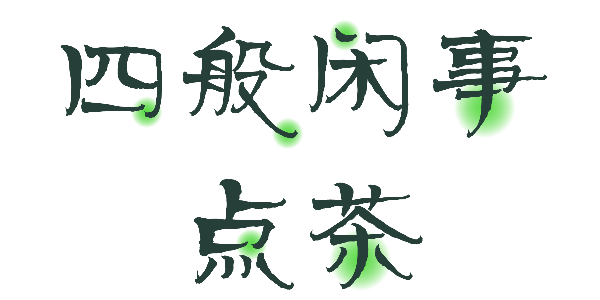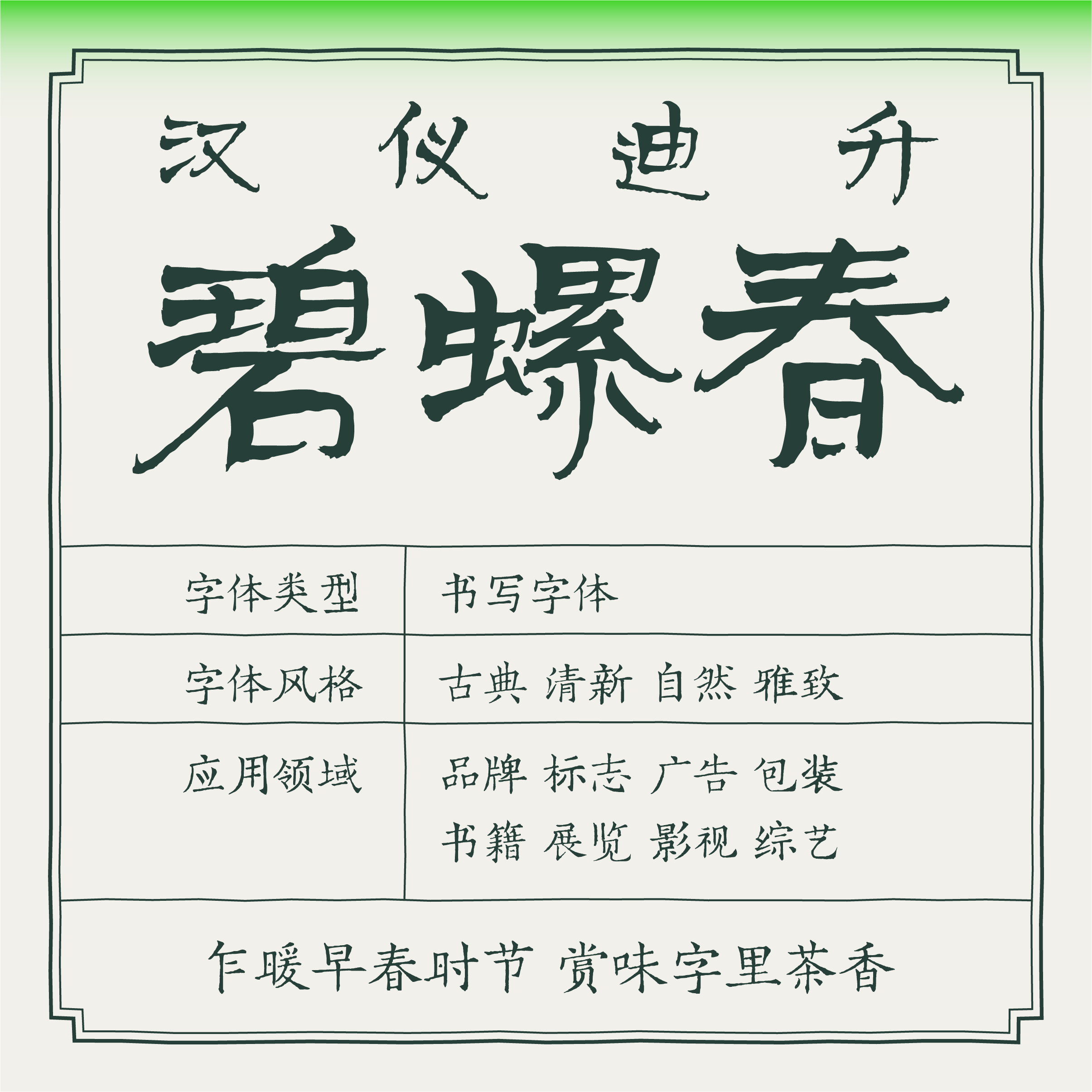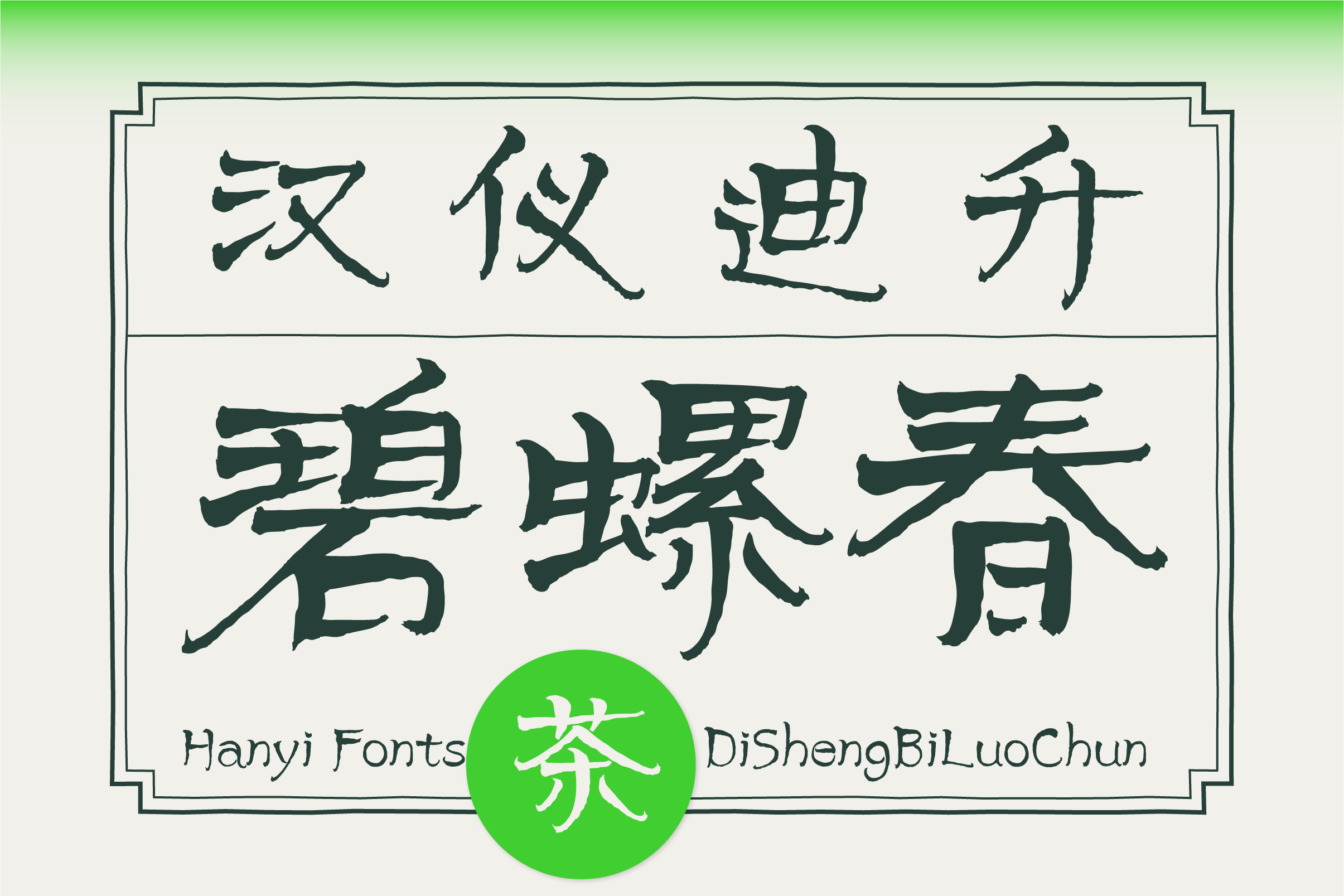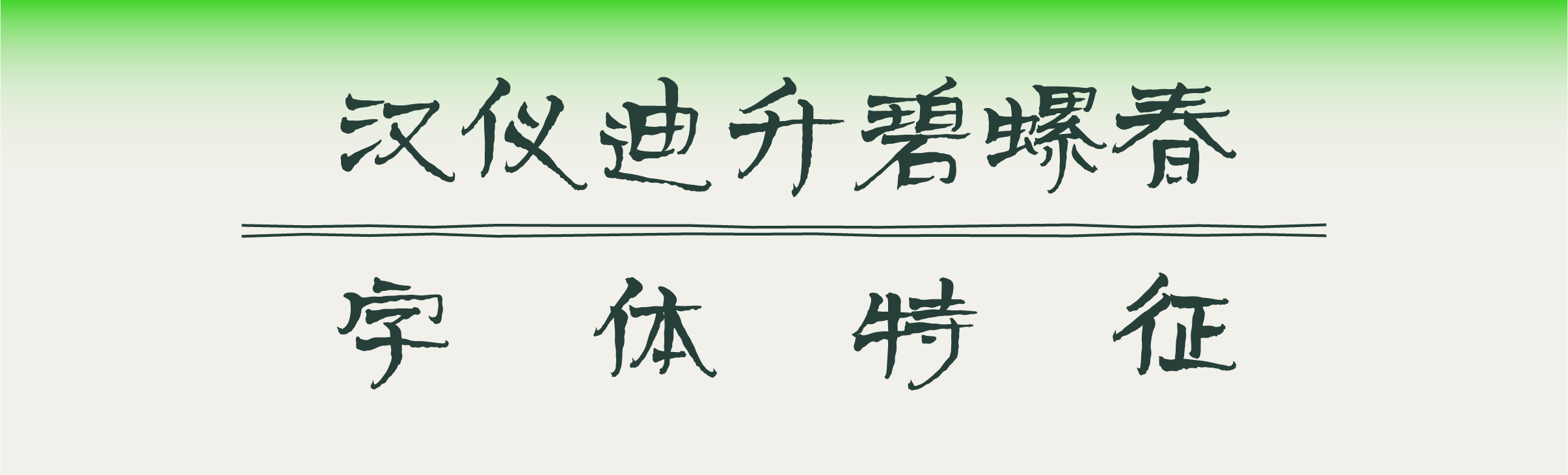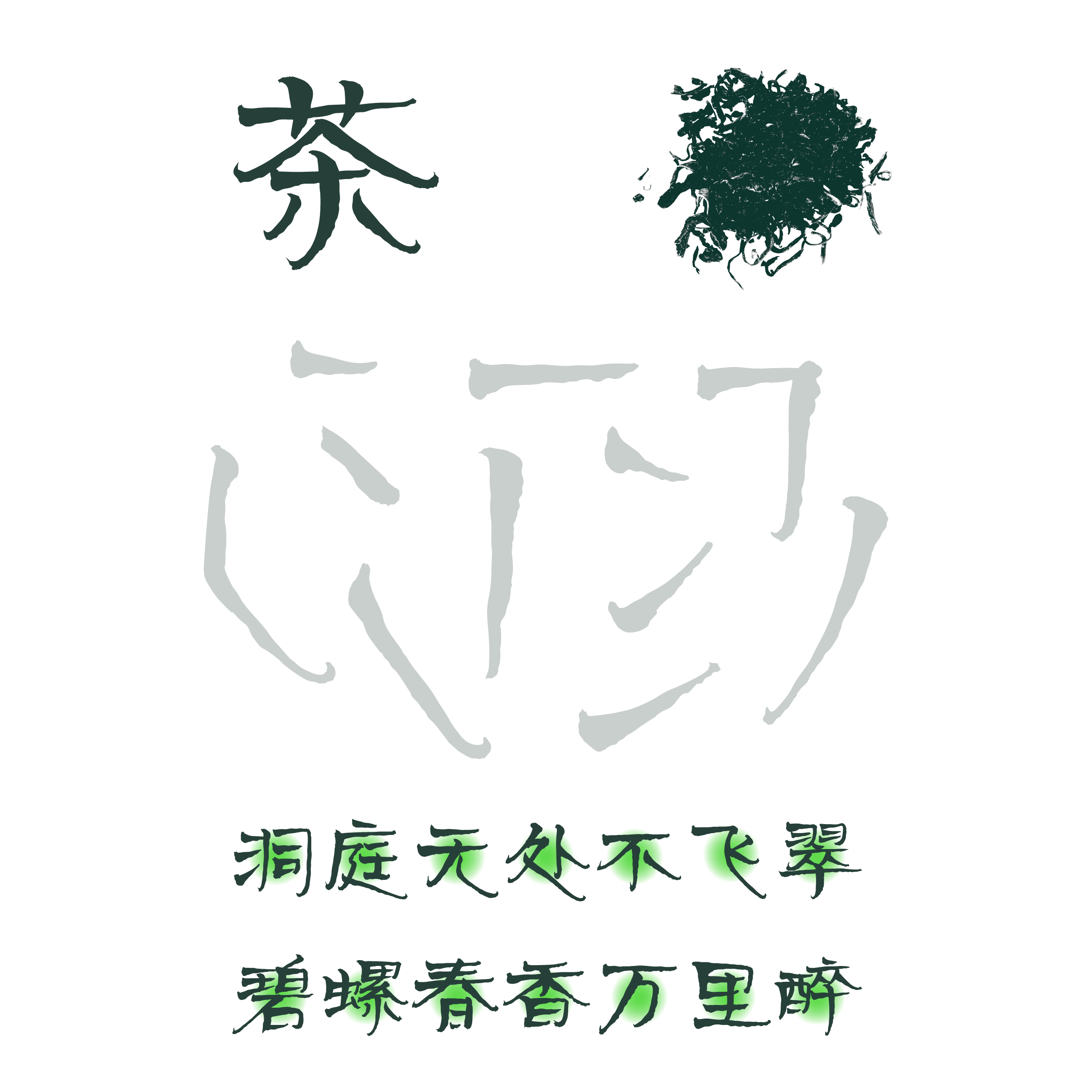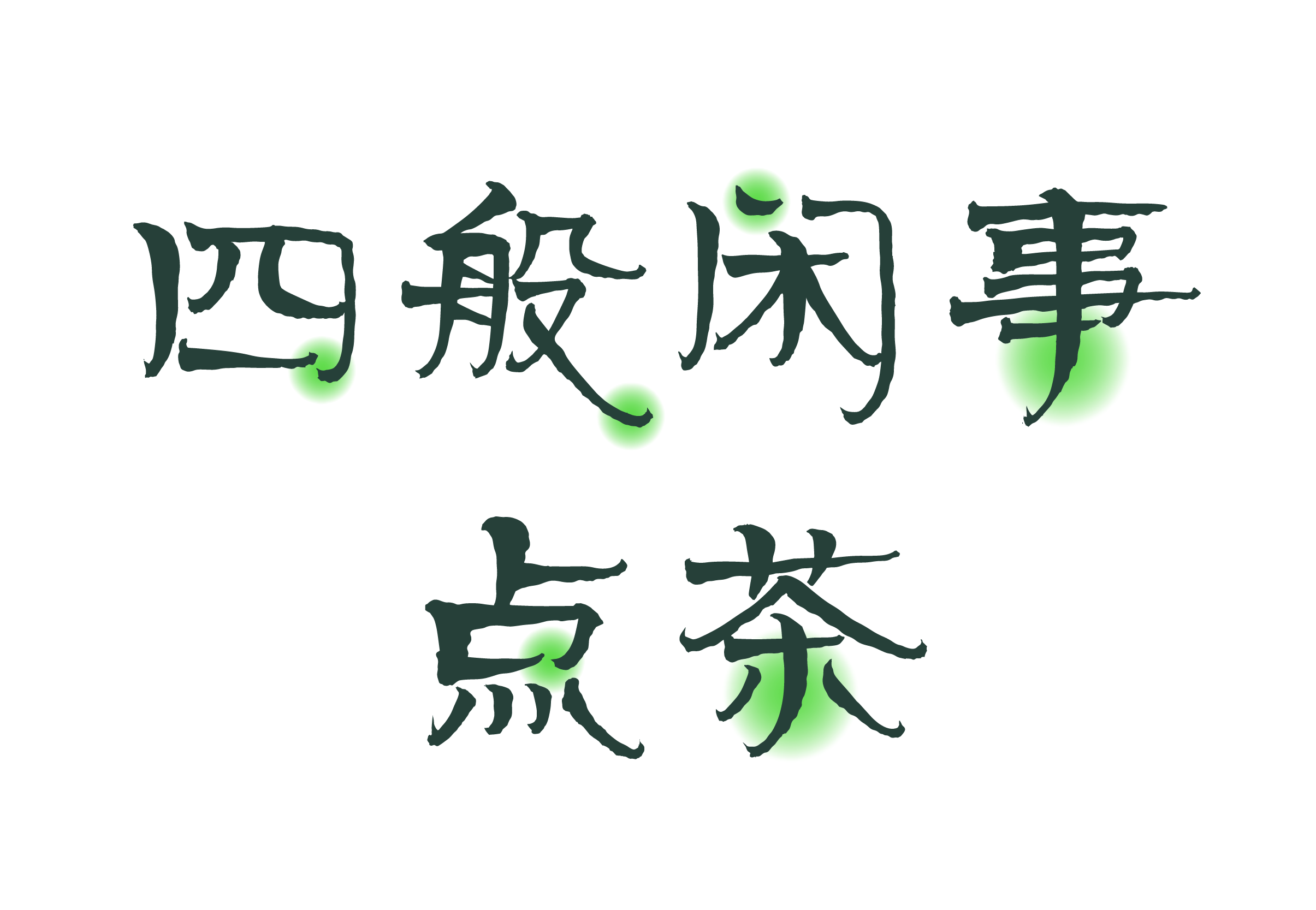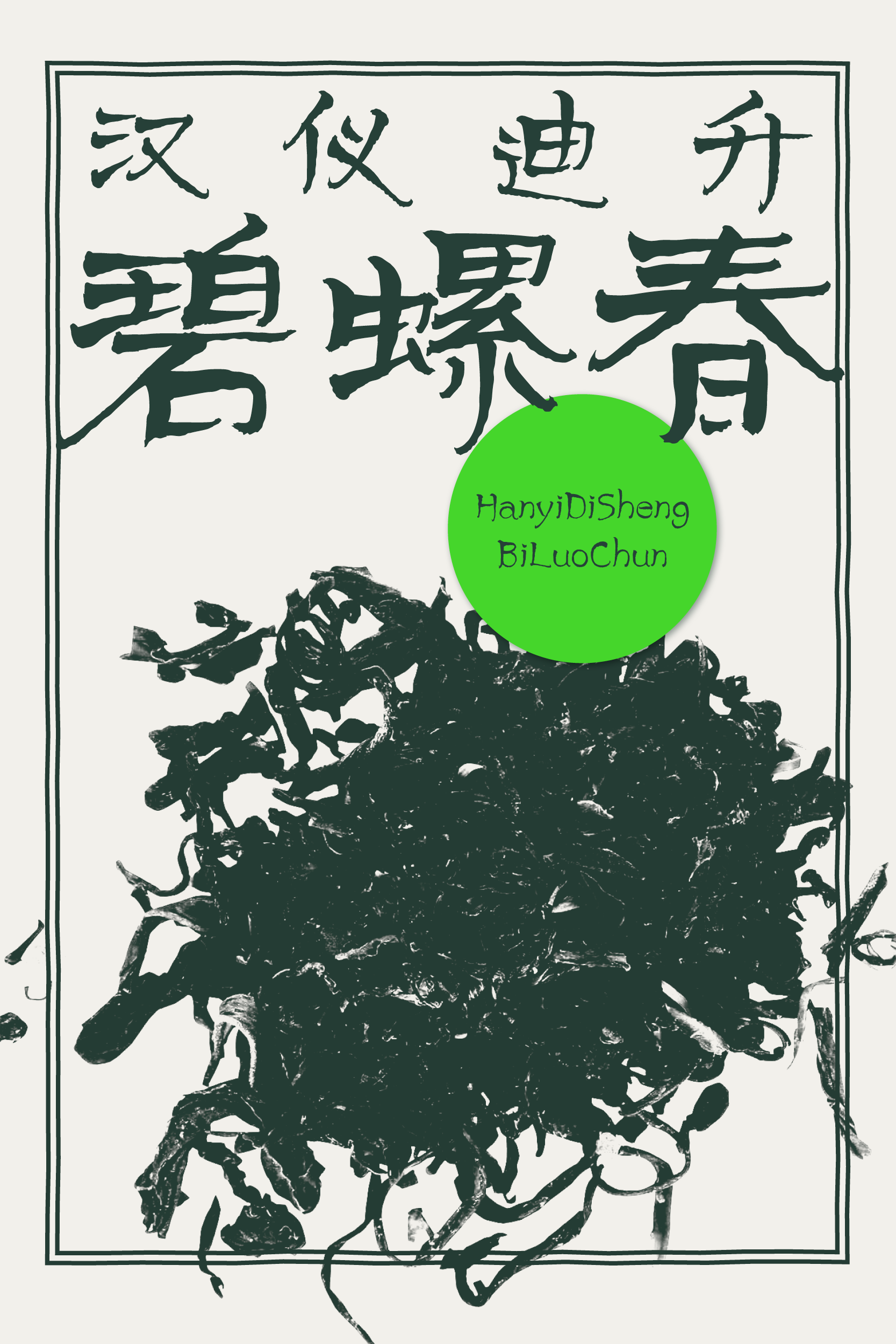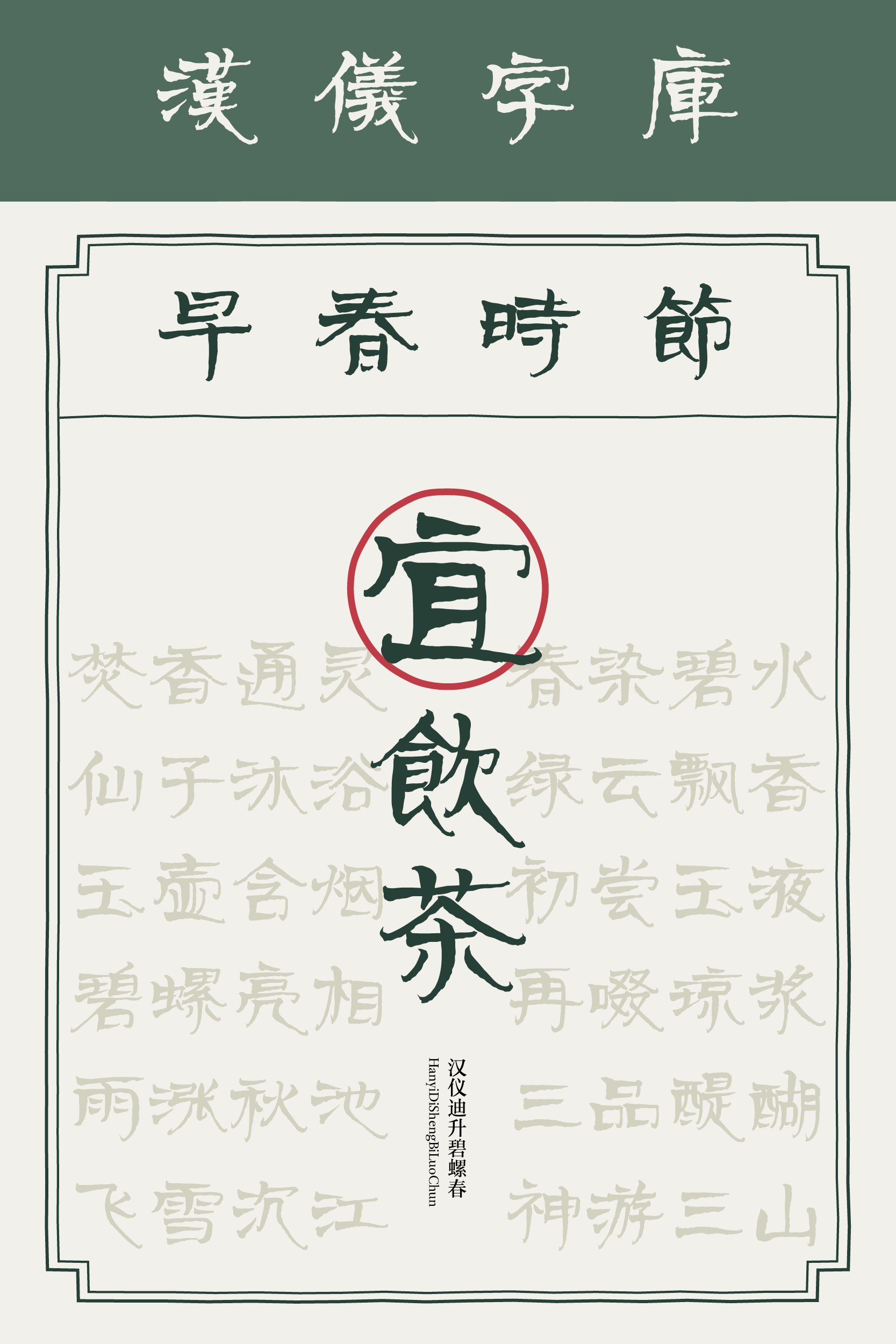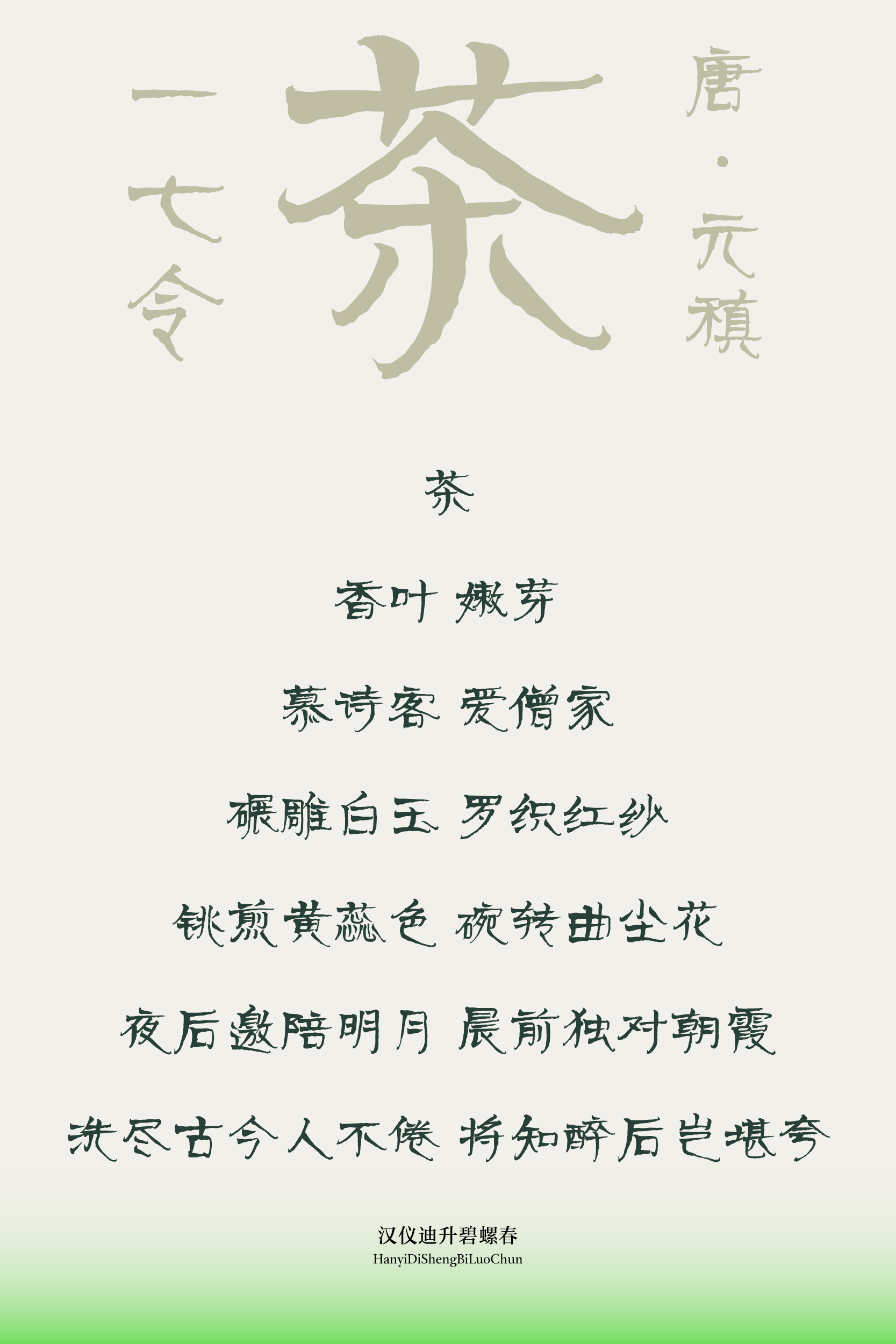
一款茶香四溢的字体
汉仪迪升碧螺春,因笔画卷曲形似碧螺春茶而得名。狼毫小楷书写,以隶书为灵感,将平入平出的书写方式与婉转颤动的笔法结合,整体风格清丽秀雅,兼具古韵与新意。适合用于传统茶叶和新式茶饮的品牌视觉、产品包装,透过字体轻嗅茶香。
以隶书为灵感,舍去蚕头雁尾,选取平入平处的书写方式。
结合婉转颤动的笔法,笔画形似碧螺春茶,条索紧结,卷曲螺旋。
书写细节丰富,卷曲、断连,清丽而随性。